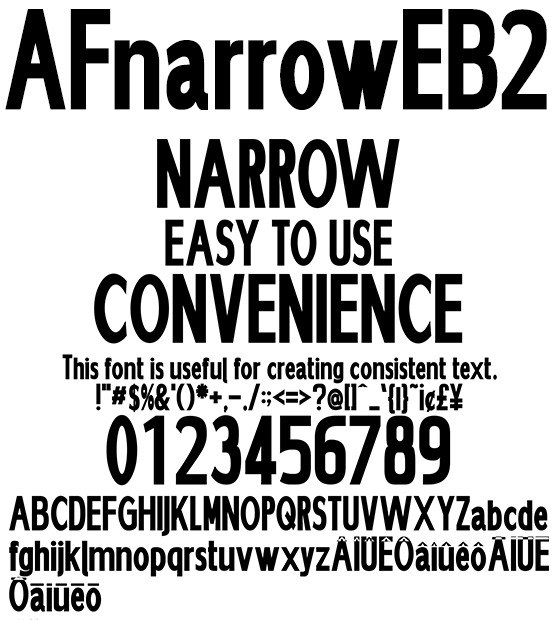
長体太字欧文 AFnarrowEB2
AFnarrowEB2
長体太文字欧文フォントです。「AFnarrowEB」よりも更に横幅を狭めました。レングスあるキーワードでも左右圧縮したフォントでインパクトある表現を維持できるでしょう。同人系、コミック、アニメ、ゲーム、リーフレット、フライヤー、ファッション系コンテンツに使える便利なフォントです。